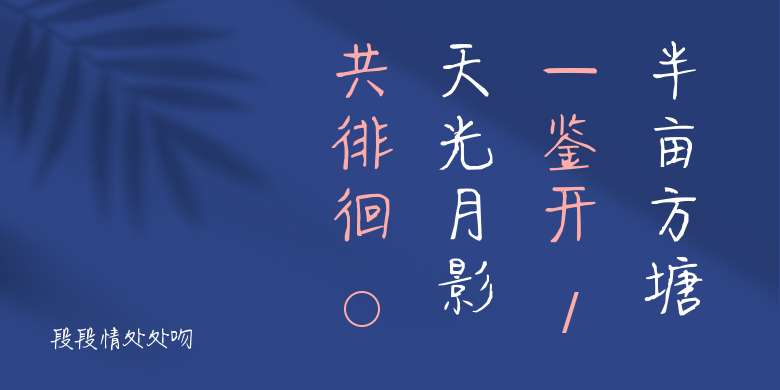
段段情处处吻
段段情处处吻,这款字体结构工整、笔画清晰,兼顾美观与易读性,适用于标题、正文、海报、包装、LOGO 等多种场景。字形优雅稳定,风格百搭耐看,适配日常排版与创意设计,让文字呈现更舒适、更具质感。段段情处处吻一笔一画,皆是细节,以均衡的比例、流畅的线条打造舒适视觉体验,字形端正大气,风格简约现代。无论是商业设计、品牌宣传还是日常排版,都能轻松驾驭,让文字更有格调与力量。段段情处处吻字体下载。